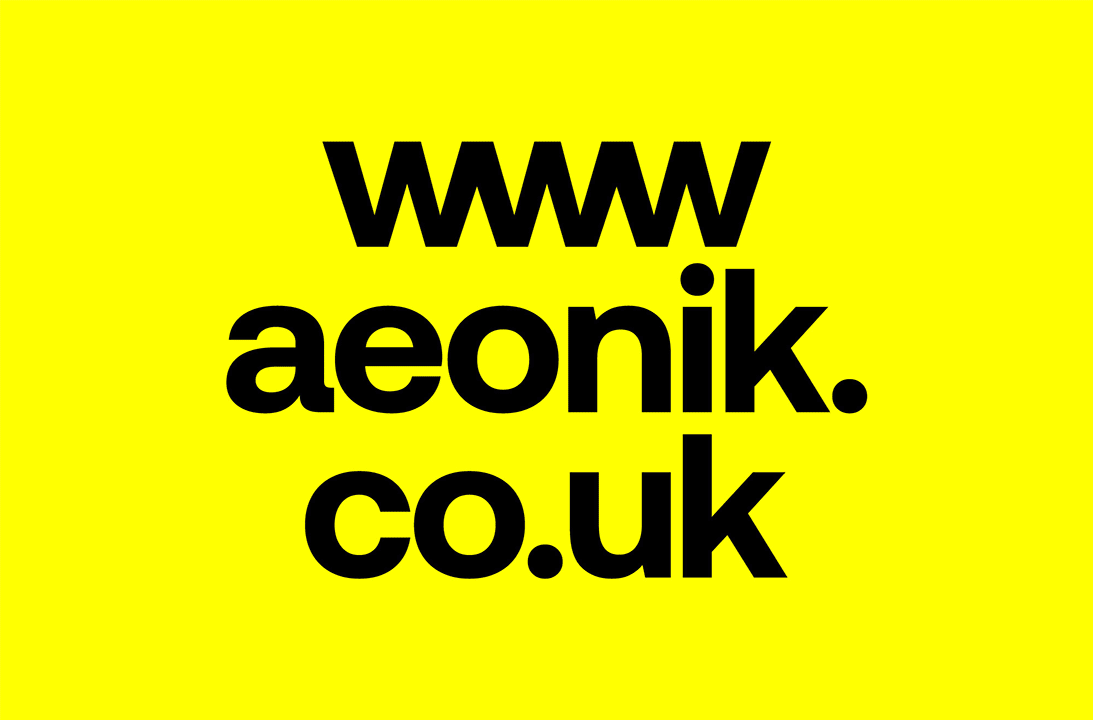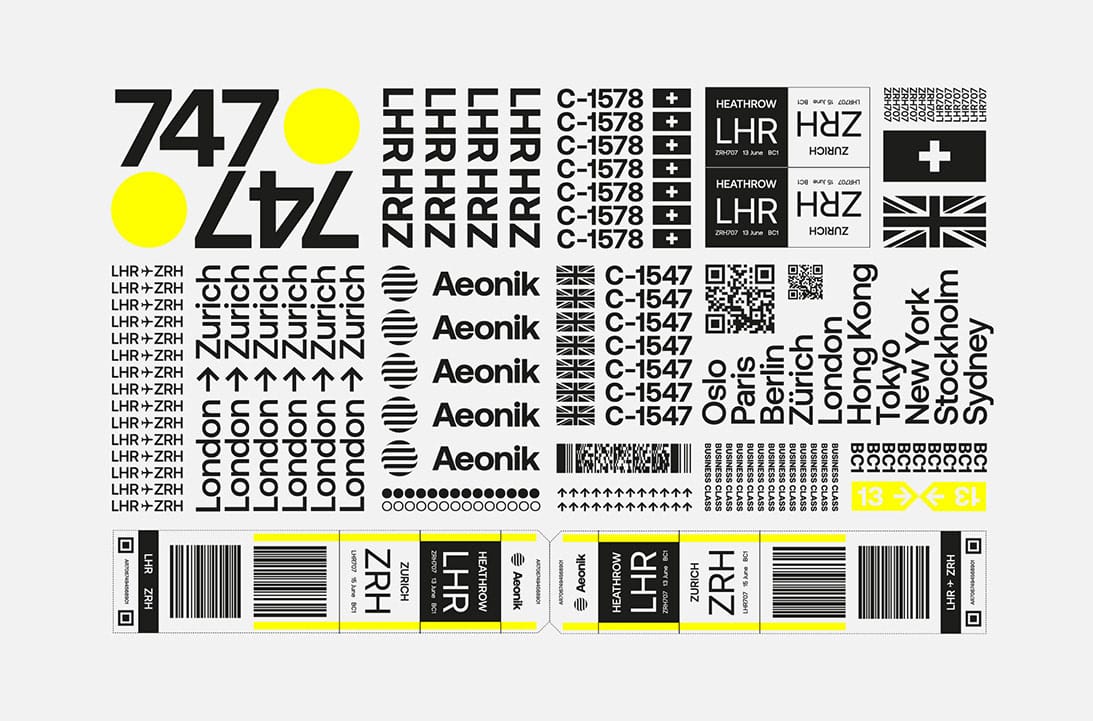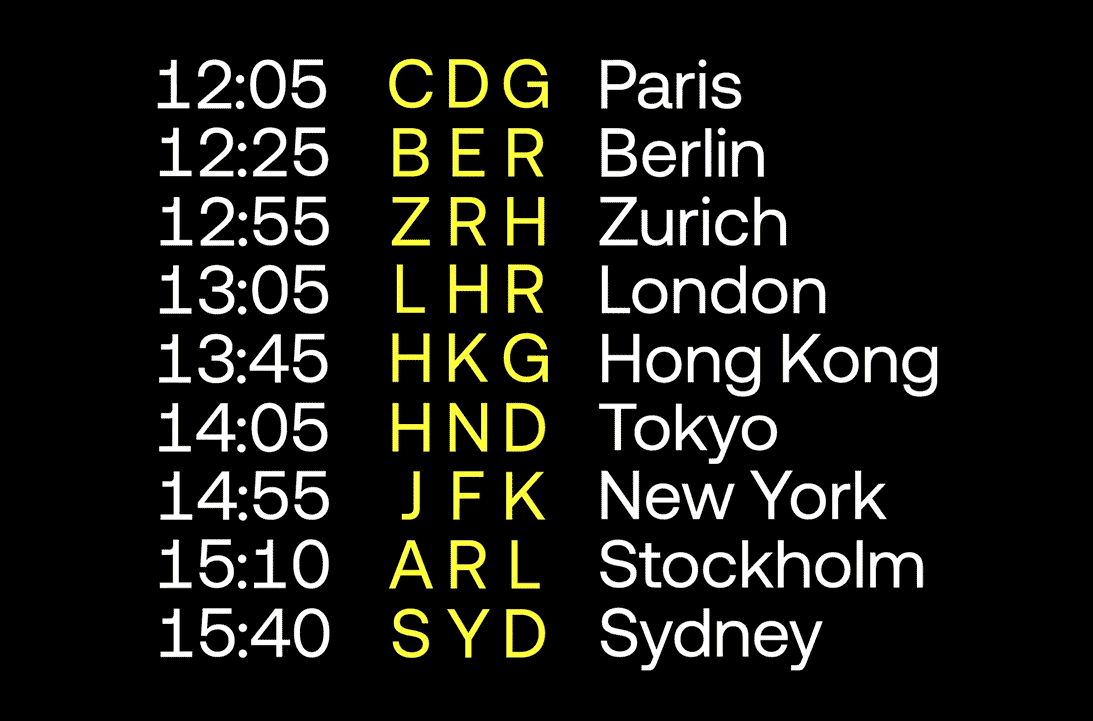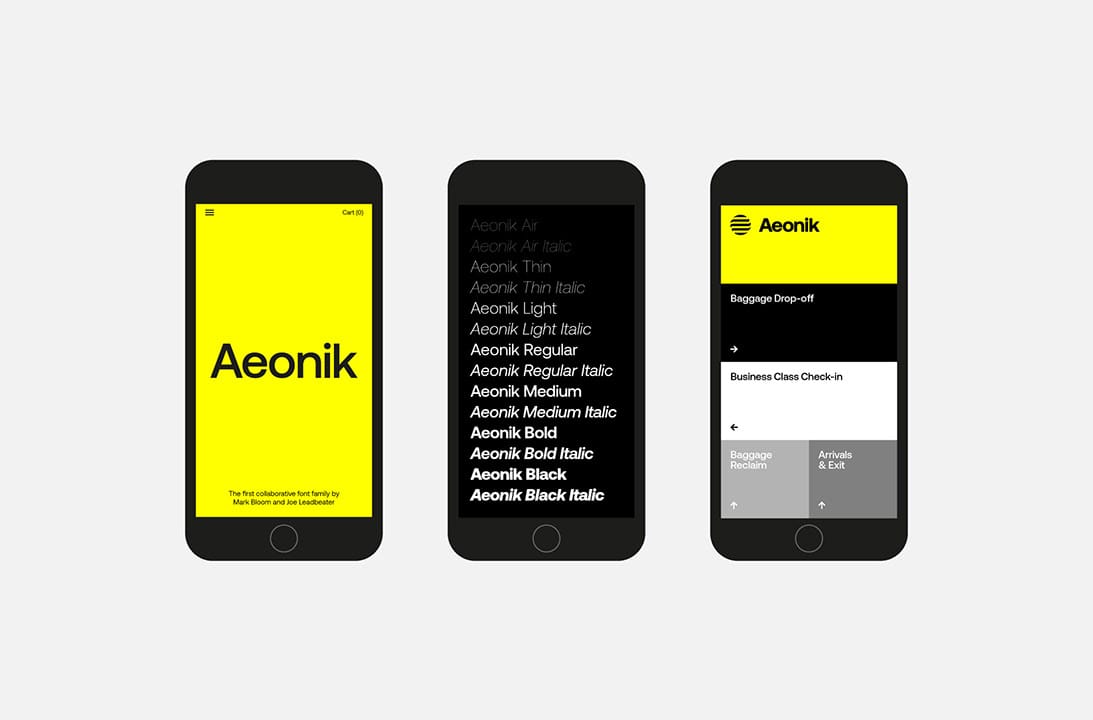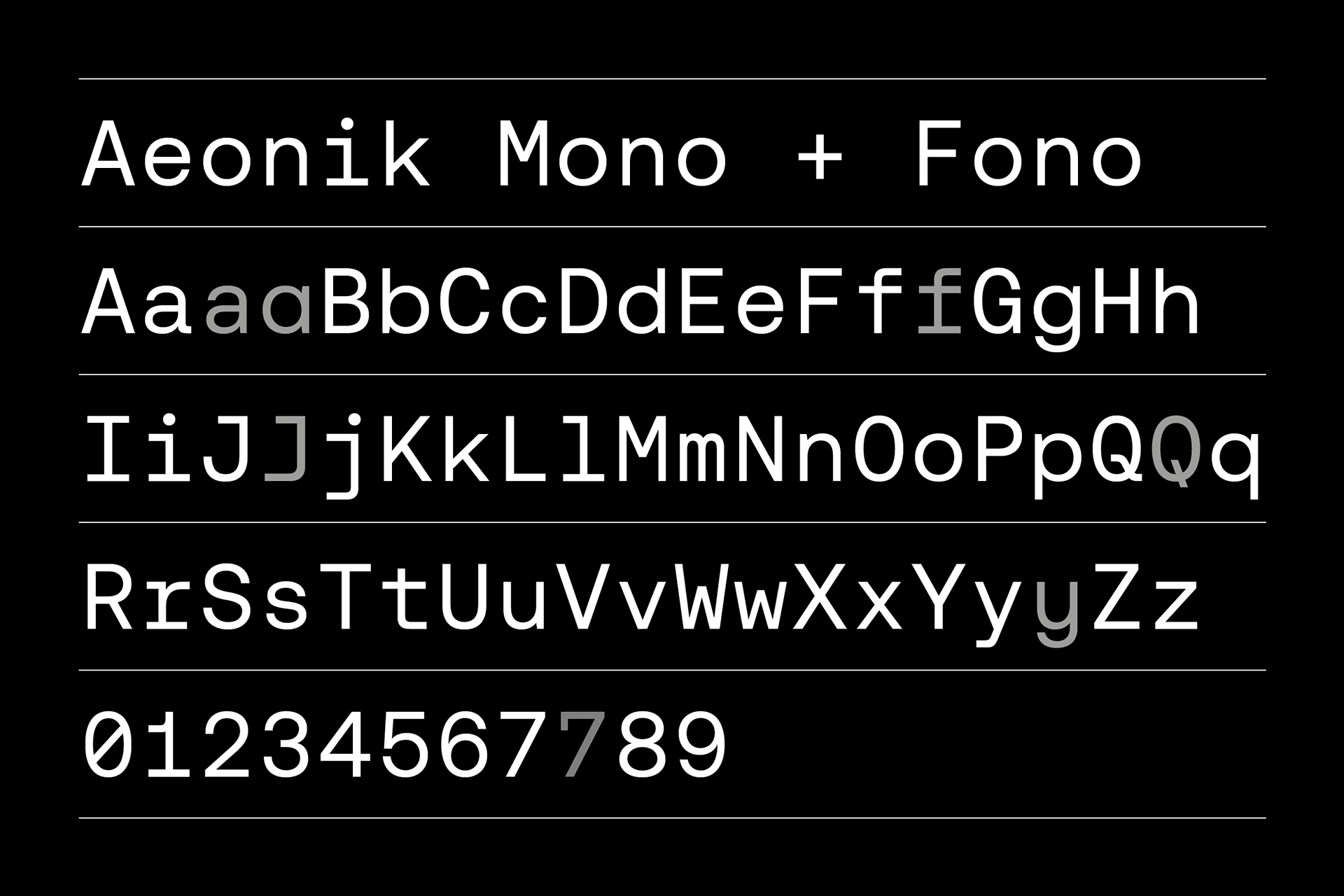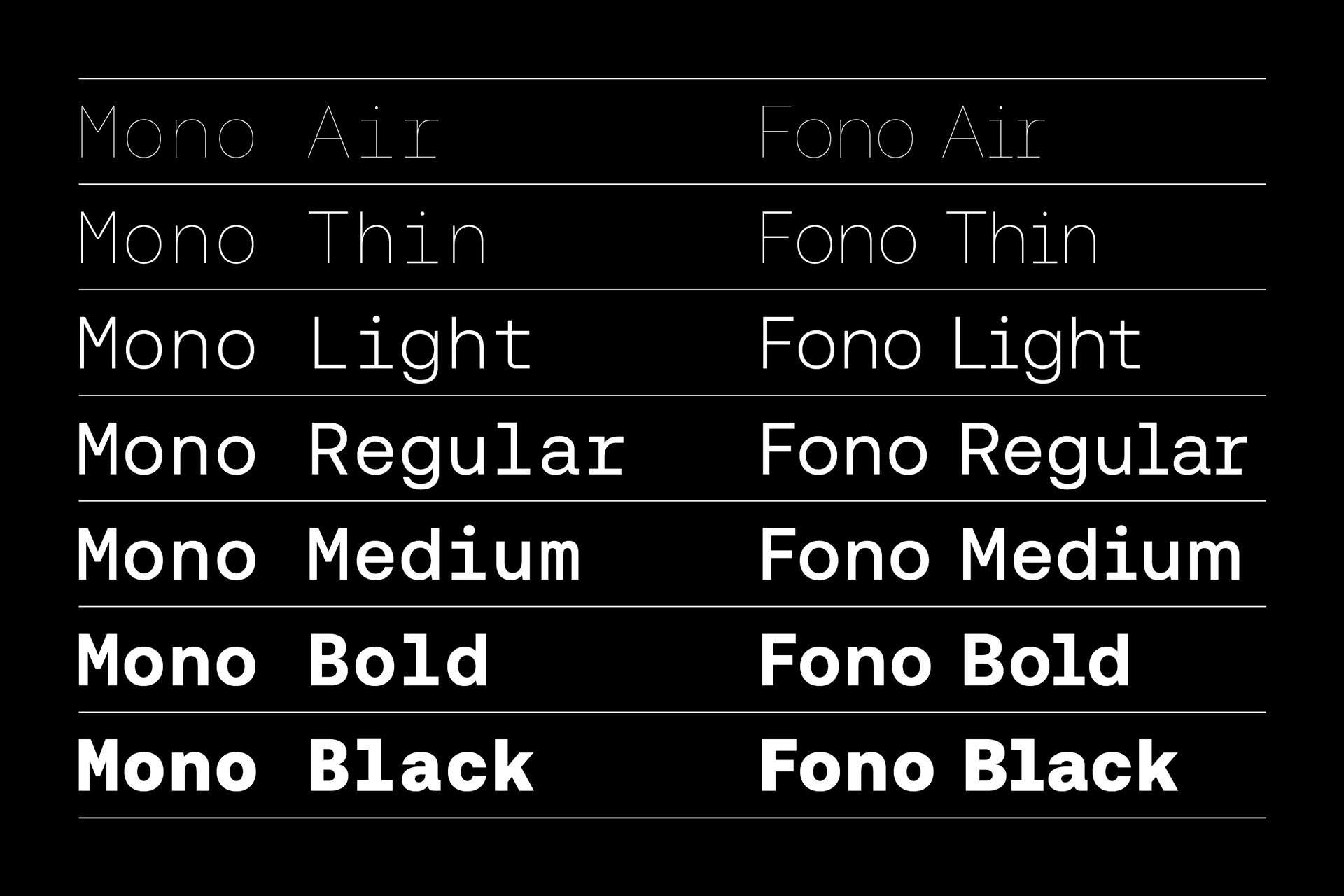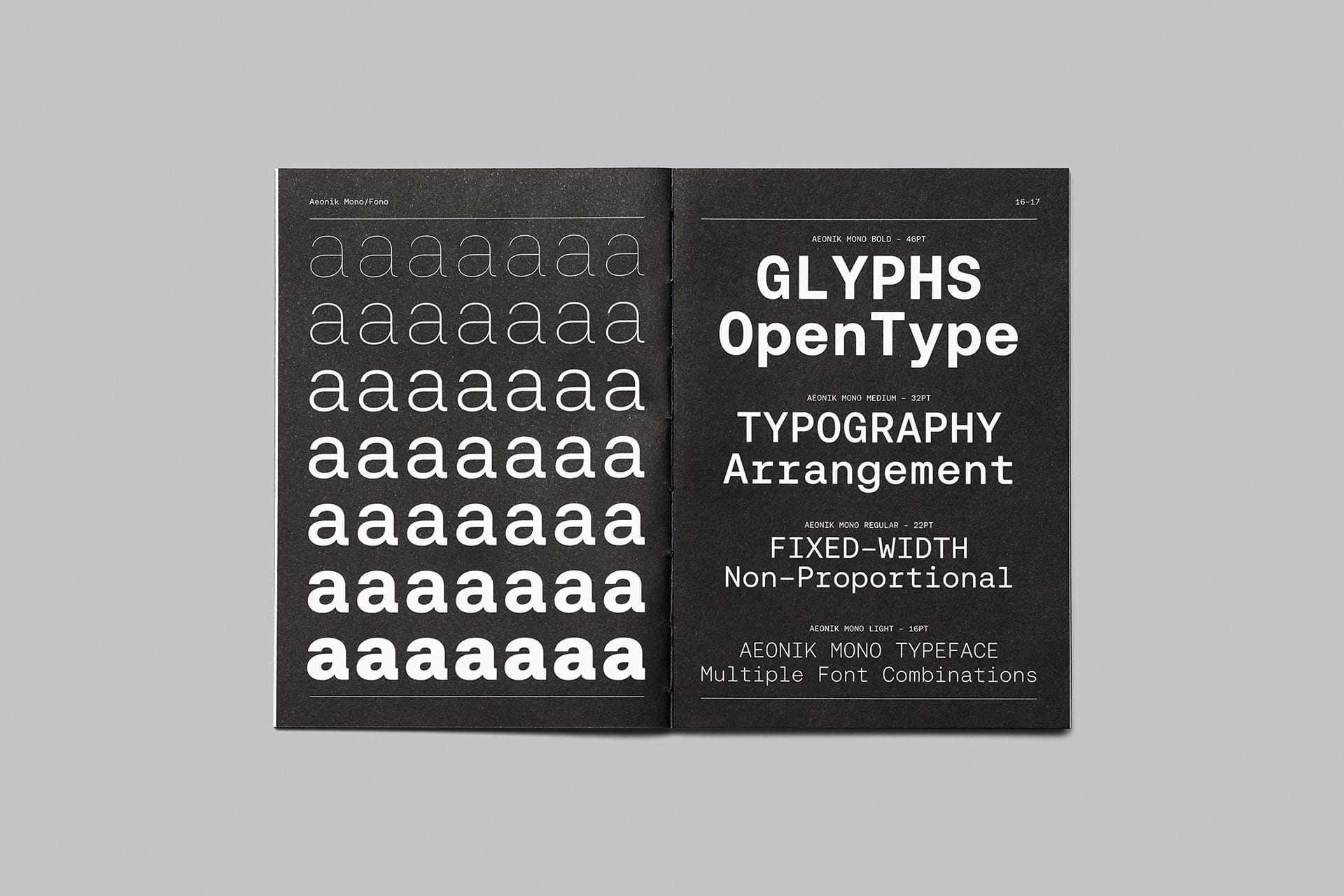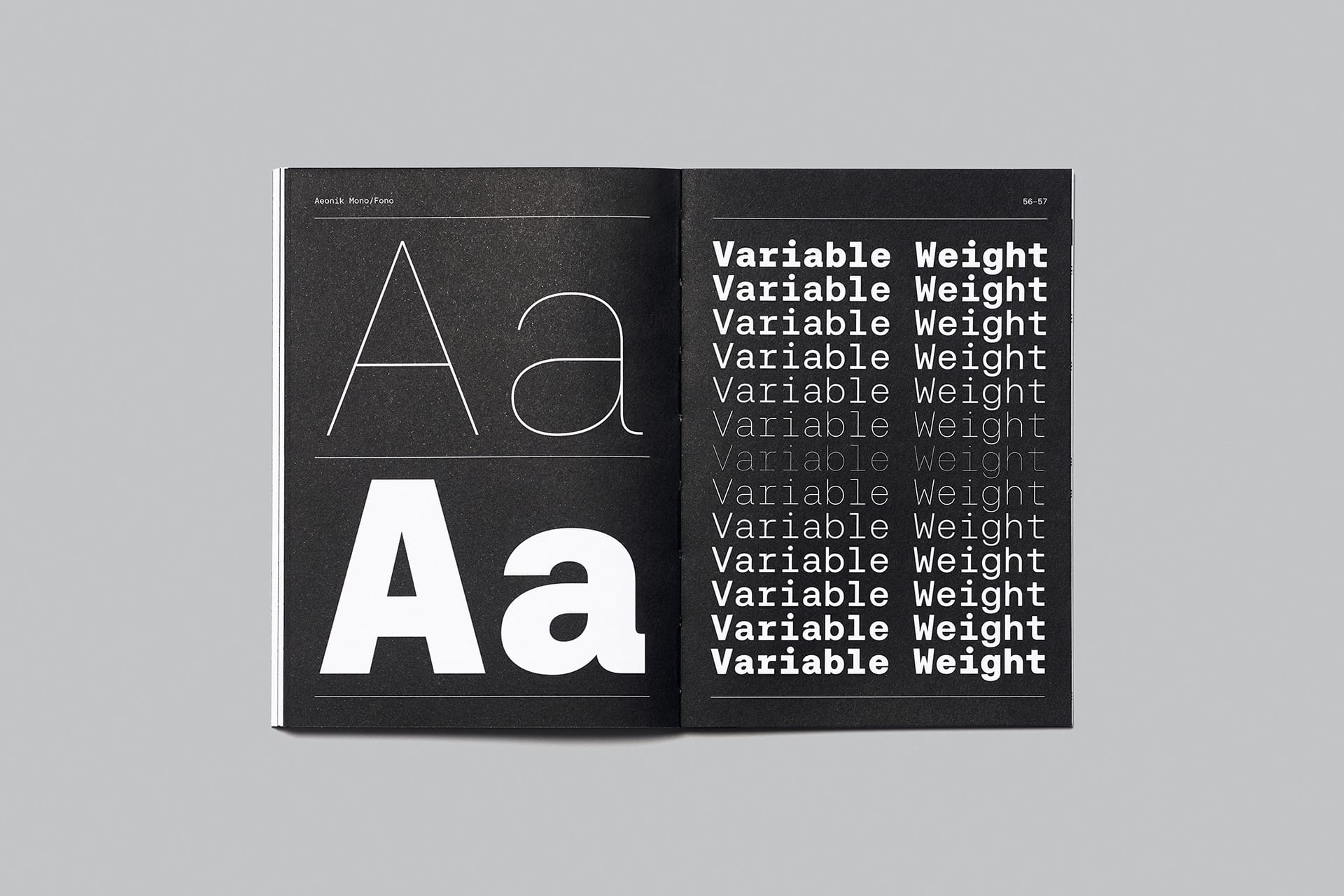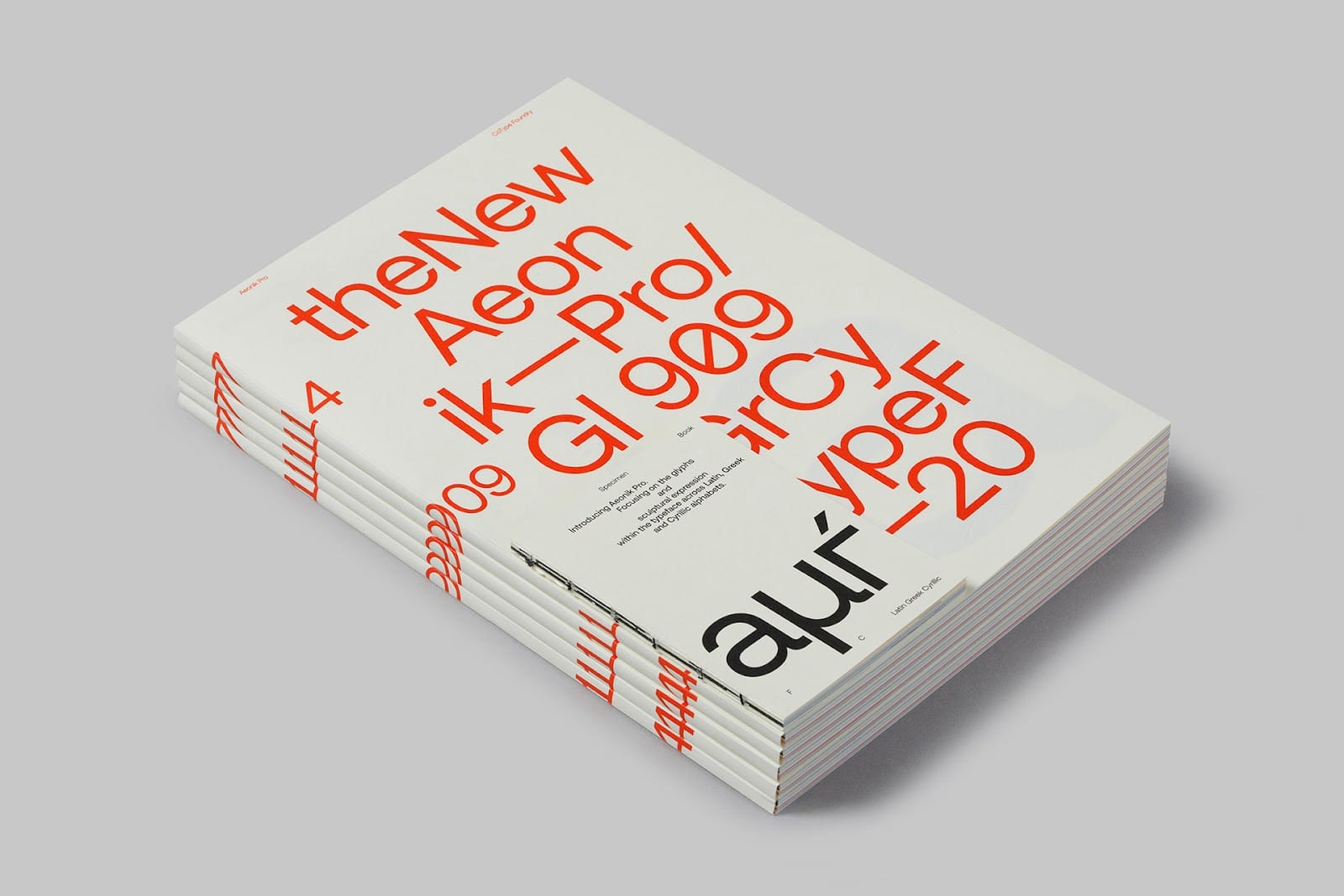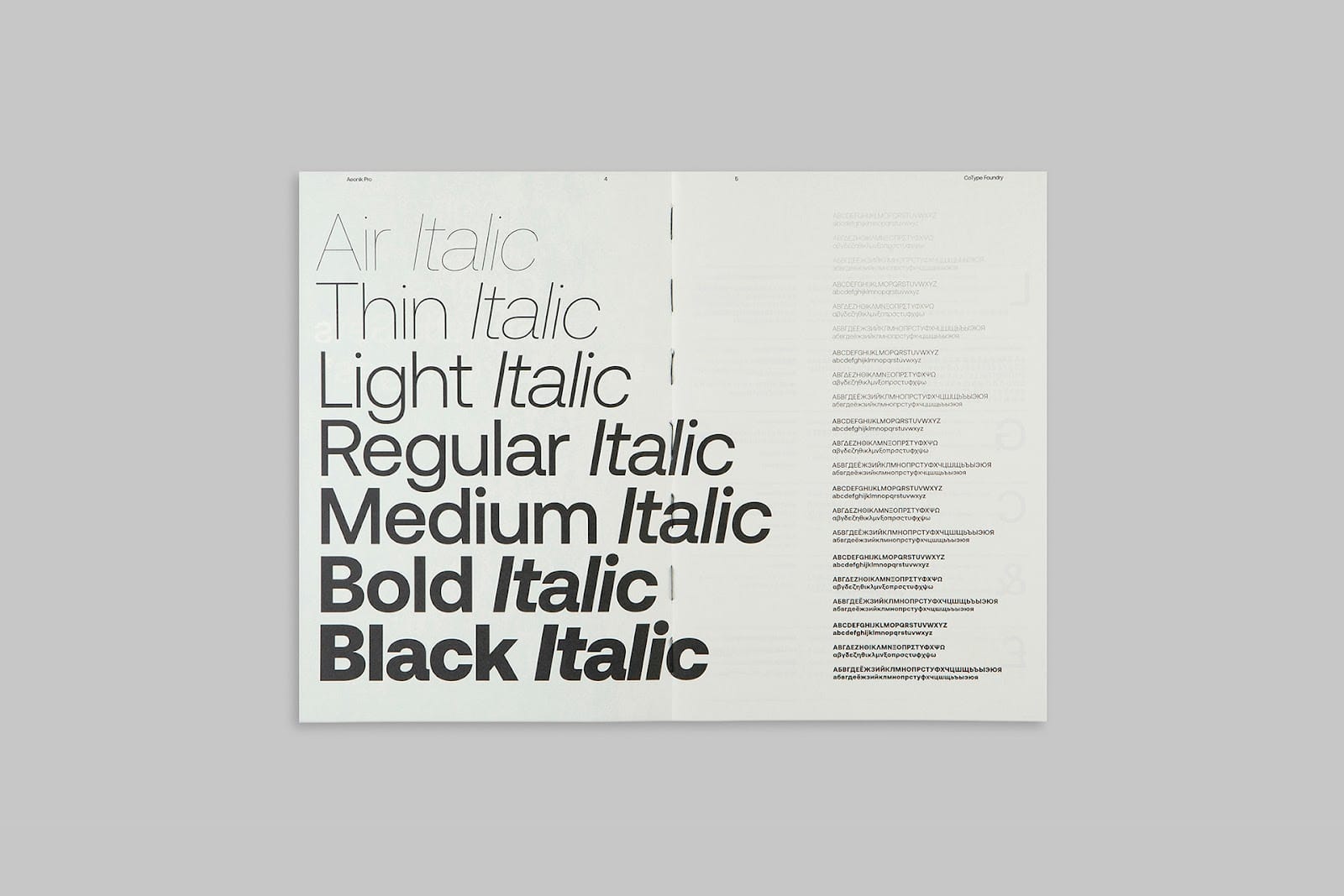
Aeonik Font Family – Là bộ font chữ chất lượng bao gồm 42 style mang phong cách hiện đại các chi tiết liên quan đến bộ font Grotesks thời kỳ đầu nhưng tỷ lệ rộng hơn và mỏng hơn. Về mặt cấu trúc, bộ font tạo ra sự cân bằng tuyệt vời cho cả việc sử dụng hiển thị và văn bản. Đây là bộ font chữ chất lượng phù hợp để sử dụng cho rất nhiều các thiết kế khác nhau.
Bộ font Aeonik cũng cung cấp các bộ ký tự rộng lớn theo từng trọng số. Các tính năng Opentype cho phép nhiều tập hợp con, thay thế chữ hoa, chữ số dạng bảng và chữ sốt lót với tỷ lệ được thiết kế tỉ mỉ.
Bộ font Aeonik Pro là một cải tiến lớn hơn so với phiên bản Aeonik trước đó, đồng thời hỗ trợ thêm cho Cyrillic và Hy Lạp. Aeonik Pro Family giờ đây sắc nét hơn, chặt chẽ hơn và linh hoạt hơn. Với hơn 900 ký tự và nhiều ký tự thay thế để lựa chọn vì vậy đây có thể là bộ font dành cho bất kỳ nhà thiết kế nào.
Bộ font Aeonik Mono và Aeonik Fono
mang đến nhiều kiểu cách, các chữ số được đóng hộp và khoanh tròn cũng như các ký tự và mũi tên thay thế, 2 bộ font này được xây dựng để người dùng có nhiều lựa chọn hơn trong thiết kế.